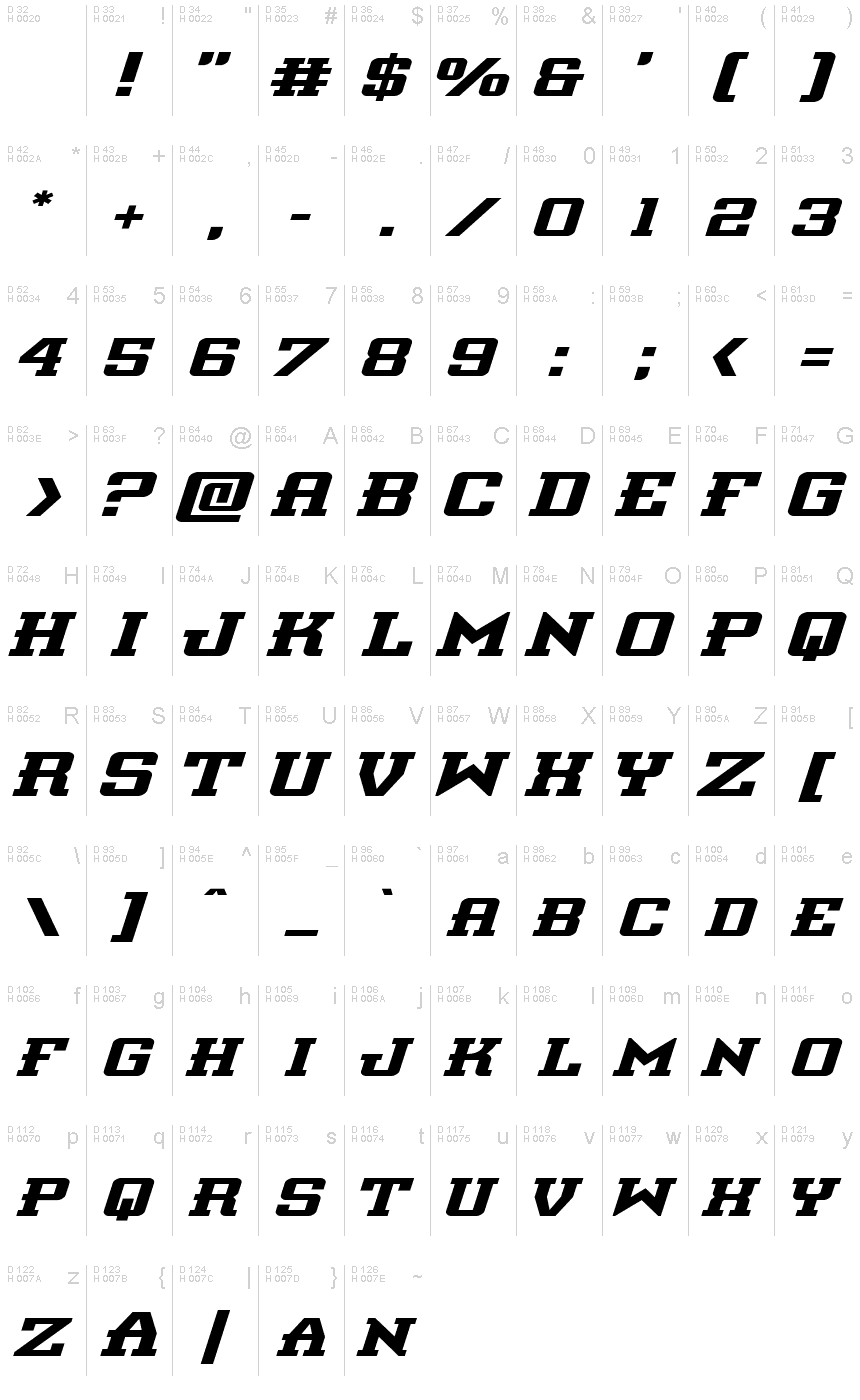
Interceptor Expanded Italic von Iconian Fonts ist eine kostenlose, futuristische Sport-Display-Schrift mit breiten, nach vorne geneigten Versalien und einem harten, comicartigen Charakter. Die Buchstaben wirken wie auf Geschwindigkeit getrimmt: Die breite horizontale Ausdehnung, scharfe diagonale Schnitte und markante Verbindungen verleihen der Schrift einen energiegeladenen Action-Rhythmus, der an Sci-Fi-Branding mit einer Prise Arcade-Nostalgie erinnert.
Sie passt perfekt zu Postern, Gaming-Logos, Streaming-Overlays, Titelkarten und Cover-Designs, bei denen es mehr auf Bewegung als auf Subtilität ankommt. Als kostenlose Schrift eignet sie sich zudem hervorragend für Team-Marken, Monogramme und plakative Verpackungsdesigns, da der erweiterte Neigungswinkel und die scharfen Ecken selbst kurzen Wörtern eine schnelle und kraftvolle Wirkung verleihen.